添加字形到阿拉伯字体
简介
在某些情况下一个字体可能缺少一个在你的应用程序中使用时必要的字形。阿拉伯字体在这里展示了特殊的问题,由于字形的形状不仅依赖于它在词中的位置,也依赖于字母本身的属性。因此(使用无意义的序列 babab),字母 beh 有三种不同的形状,依赖于是否处于开头、中间还是结尾。然而(使用无意义的序列 dadad),字母 dal 只有一个形状,而无论其处于词中的什么位置。
本章介绍为一个阿拉伯字体添加一个字形。我们将使用的字体是 Graph,我们将添加的字形是 peh(U+067E),它在阿拉伯字体中并不出现,但是在使用阿拉伯书写字母的一些语言中指定 p(阿拉伯书写字母的字形全列表参见 Unicode 图表)。
制作字体的工作副本
从网页下载并字体并解压。运行 FontForge 并加载字体。将其保存为 sfd,在保存前编辑建议的名字来读取 GraphNew.sfd。
重命名字体
为什么要重命名字体?
如果你不重命名字体,你修改的字体将不会与原始的区分开安装——你将不得不首先卸载原始字体。如果你准备分发你的修改版的时候重命名字体也是明智的——如果字体原作者使用 Reserved Font Name(RFN)机制保留了字体名,那么原始名字只能用于原作者的字体版本。
修改名称数据
选择Element->Font Info,在 PS Names 面板下将 Fontname,Family Name 和 Name For Humans 修改为 GraphNew。
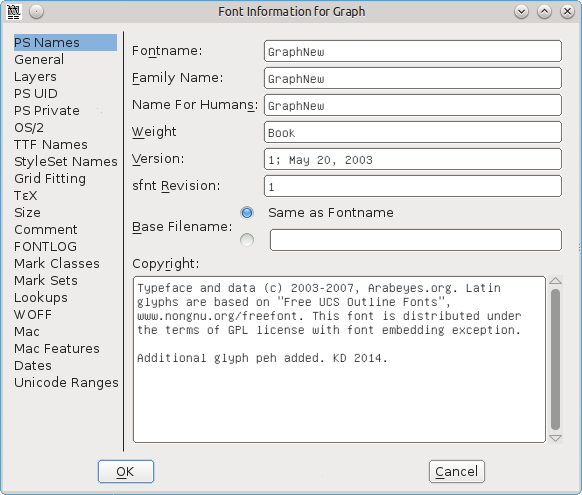
如果有必要,你可以在 Copyright 一项的文本后添加一条信息“Additional glyphs added by”。
在 TTF Names 面板下的,tFamily 和 Fullname 的名称取自 PS Names 一项,应该显示的是 GraphNew(你不能直接编辑他们)。将 Preferred Family 和 Compatible Full 两项修改为 GraphNew。现在如你所希望的那样,这些名称的修改将会允许你将字体与原始字体安装在一起。
如果有必要,你可以在 Designer 一项的文本后添加一条信息“Additional glyphs added by”。
点击 OK 来保存修改。你将会看到一条关于为字体生成一个新的 UniqueID(XUID)的消息——点击 Change。
为 peh 的孤立形式添加字形
打开字体图表的阿拉伯区域:选择 View->Go to,点击下拉框并选择 Arabic,然后点击 OK。
点击字体图表中的一个单元格将会在面板顶部用蓝色显示其 Unicode 数字和名称。转到位置 1662,将会显示蓝色的 1662 (0x67e) U+067E "uni067E" ARABIC LETTER PEH。引用的字形下面的单元格包含一个灰色的 X,意味着字体并不包含这个字形。
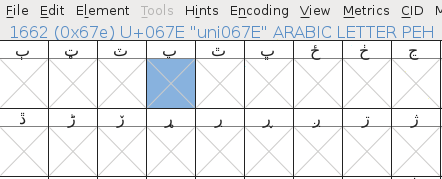
我们将通过复制 beh(U+0628)并将其一个点替换为三个点来制作 peh。
点击 beh 单元格(位置 1576),然后右击并选择 Copy。然后右击 peh 单元格并选择 Paste。现在 beh 被复制进 peh 单元格,接下来要修改的是点。
找到一个包含三个点的字形——sheen(位置 1588,U+0634)符合。双击这个单元格——将会打开一个字形设计面板。按 V 来确保工具箱的指针工具(剪头)选中,按 Z 扩大面板来给你一个字形的好的视图。
点击拖动 sheen 上的三个点的节点,颜色从粉色变为米色。如果你意外地包含或者忽略了一个节点,那么取消选择或者通过按 Shift 并点击来选择。按 Alt+C 来复制。
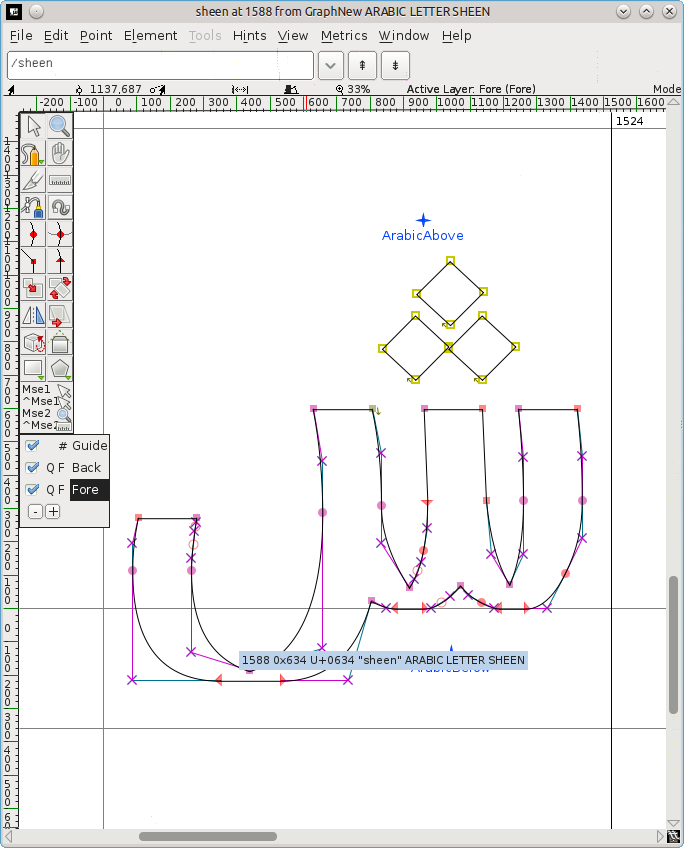
返回字体表格并双击 peh 单元格——这会将 peh 加载到字形设计面板 sheen 选项卡旁边的另一个选项卡。
点击拖动来高亮 peh 下面的点,然后按 Delete。按 Alt+V 来粘贴三个点,很可能出现在 peh 主体的上面。留下高亮的点的节点,这样你可以很容易地翻转或者移动它们。
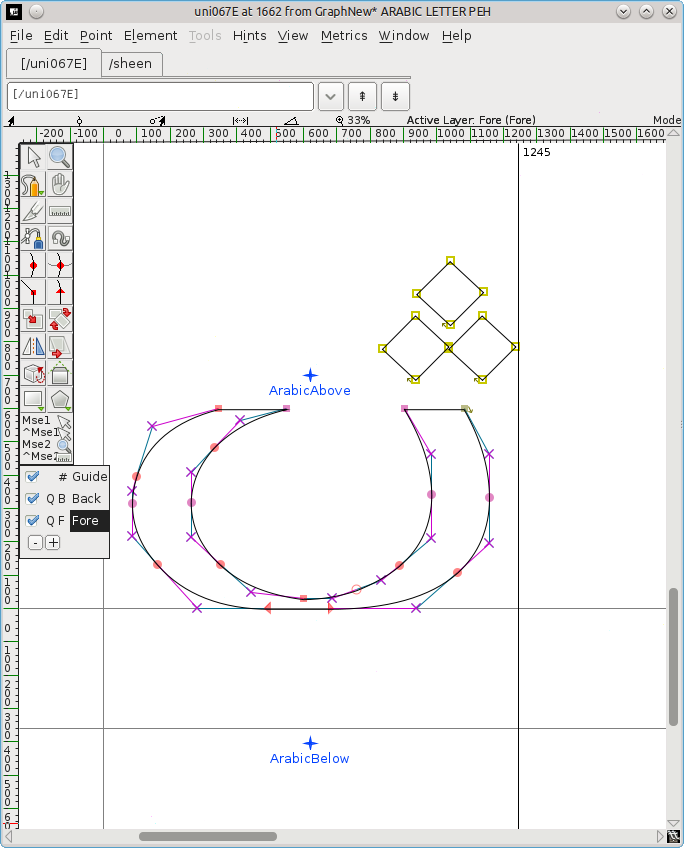
翻转点:从工具箱选择翻转工具(两个三角形中间有一条红色虚线)。(也可以右击点的中间,从弹出菜单中选择 Flip the selection。)点击点的节点中的一个,轻微向左或右拖动鼠标。
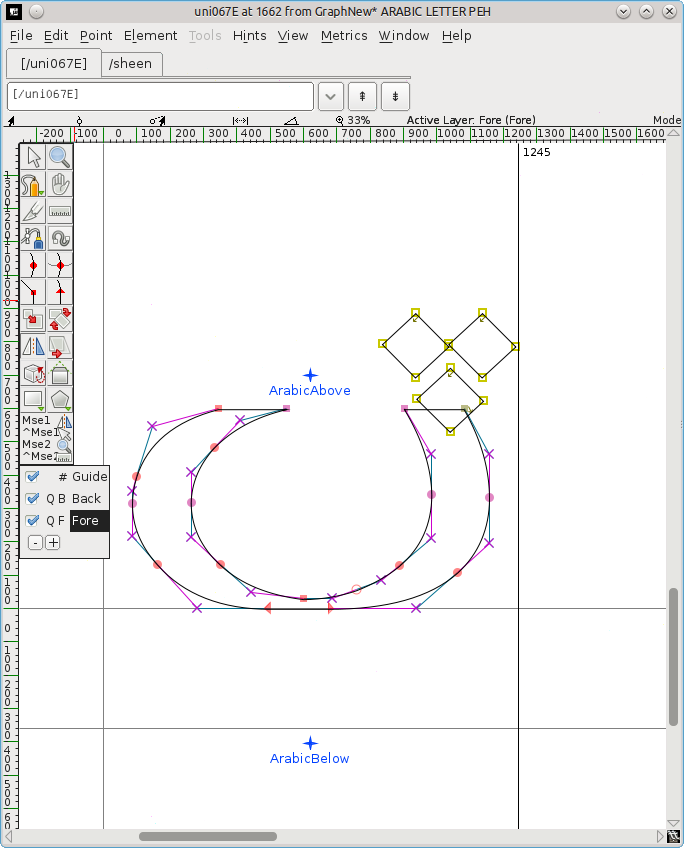
移动翻转的点:按 V 来再次选择指针工具,点击点的节点中的一个,然后将其拖动到字形主体的下面。将他们放在 ArabicBelow 标记上的中间位置。
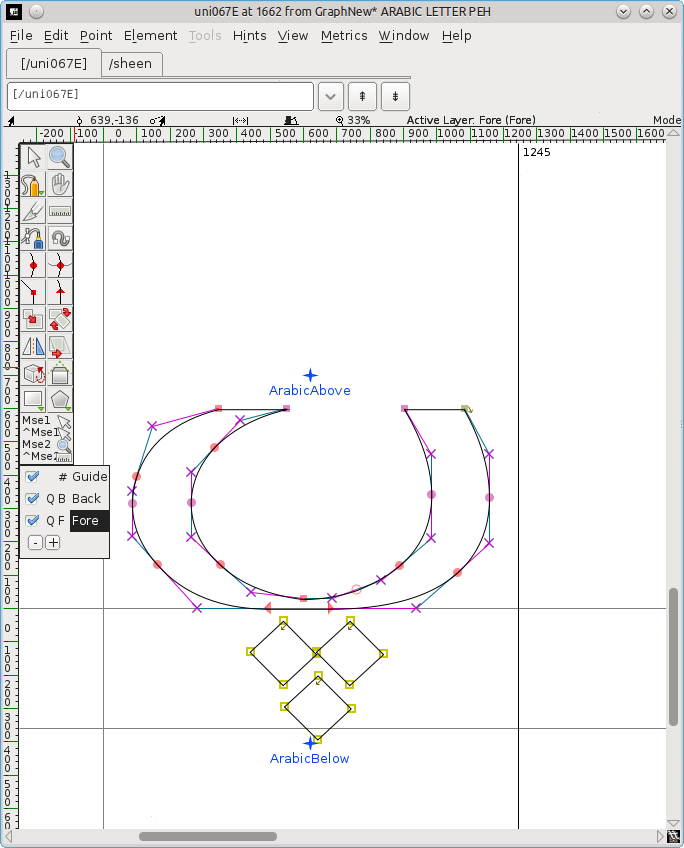
关闭字形设计面板。现在字体表格中的 peh 应该有一个新的字形。保存修改的字体(File ->Save)。
为 peh 的连接形式添加字形
但是这只是字形的孤立(独立)形式。如果你尝试使用你修改过的字体,你将会发现开头、中间和结尾形式并不可用。它们必须被分开制造。“这些形式作为未编码字符(FontForge 约定编码是 -1 的字形)来构建。它们没有预定义的位置。”(Khaled Hosny)
选择 Encoding->Add Encoding Slots 并输入你想要的字形的数量——在这种情况下是 3。FontForge 将会在字体的后部添加同样数量的位置,你将会被移动到字体表格中那个位置。最后三个单元格(位置 65537,65538,65539)的引用字形处有一个问号,在这些单元格中你将会通过重复上面的流程添加未编码字形。
需要注意的是如果你在字体表格仍然拥有叫点的时候错误地开始输入,你会移动到顶部的 European 区域。要回到底部,选择 View->Go to,点击下拉框并选择 Not a Unicode Character,然后点击 OK。
创建最终形式
向上滚动一点字体表格直到你向前到达位置 65152(U+FE80)的一系列阿拉伯字形。在 U+FE90(位置 65168)你讲看到一个 behfinal 字形——点击它并按 Ctrl+C 来复制它。向下滚动到表格的倒数第三个单元格(位置65537),点击它,并按 Ctrl-V 来粘贴 behfinal 字形。
右击单元格并选择 Glyph Info。命名规范是使用孤立字形的数字 + 一个形式的后缀,因此将 Glyph Name 修改为 uni067E.fina,然后点击 OK。引用单元格的问号将会修改为 peh。
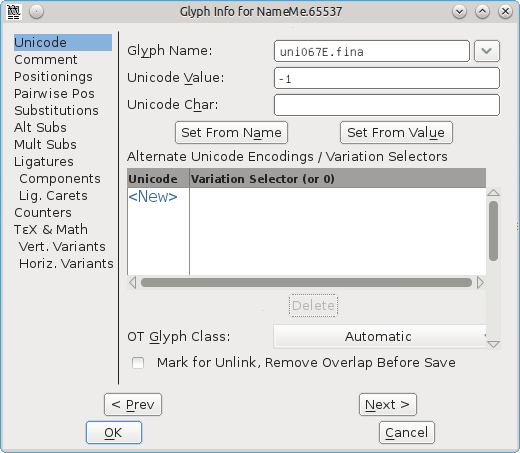
得到三个点:双击 sheen(U+FEB5)来将它加载到字形设计面板,选择三个点并按 Ctrl+C。
双击新的 pehfinal 来将它加载到字形设计面板,点击拖动来高亮点的节点并按 Delete。
Ctrl+V 来插入来自 sheen 的三个点,翻转它们,将它们移动到字形主体以下的位置。按来保存修改过的字体表格。
创建开头和中间的形式
复制初始形式 U+FE91(位置 65169)到倒数第二个单元格(位置 65538),删除单个点并粘贴三个点。
右击单元格,选择 Glyph Info,将 Glyph Name 修改为 uni067E.init,并点击 OK。
复制中间形式 U+FE92(位置 65170)到最后一个单元格(位置 65539),删除单个点并粘贴三个点。
右击单元格选择 Glyph Info,将 Glyph Name 修改为 uni067E.medi,并点击 OK。
选择 File->Save 来保存修改过的字体表格。
添加查找
孤立的形式必须被映射(连接)到它的开头、中间和结尾形式。
选择 Element->Font Info->Lookups。
点击'init' Initial Forms in Arabic lookup 2 旁边的+。这将会打开同名的子菜单。点击这个子菜单。
右边的 Edit Data 按钮现在将会变成可用——点击它。
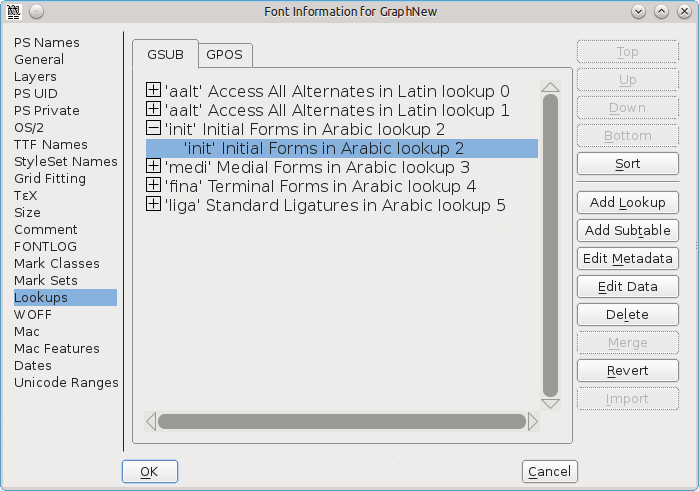
在弹出的 Lookup Subtable 面板中,确保 Unicode 按钮勾选。将字符列表向下滚动知道最后。
在 Default Using Suffix 旁边的输入框里,输入相关的后缀(在这种情况下是 init),然后点击 Default Using Suffix。
一个新的映射将会被添加到字符列表,从 uni067E(peh 的孤立形式)到 uni067E.init(初始形式)。点击 OK。
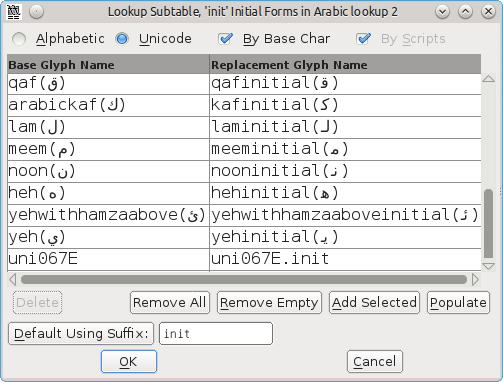
对'medi' Medial Forms in Arabic lookup 2 和'fina' Terminal Forms in Arabic lookup 2 下的子菜单做同样的操作,选择 medi 和 fina 作为相关的后缀。
再次点击 OK 来关闭面板,并保存字体表格(Ctrl+S)。
需要注意的是 Default Using Suffix 看起来只能工作在 Unicode 06(Arabic)块——在 Unicode 07(Arabic Supplement),比如带两个点的 ain,可能必须通过点击带行标记的 New 并输入名称来手动添加。
生成修改的字体